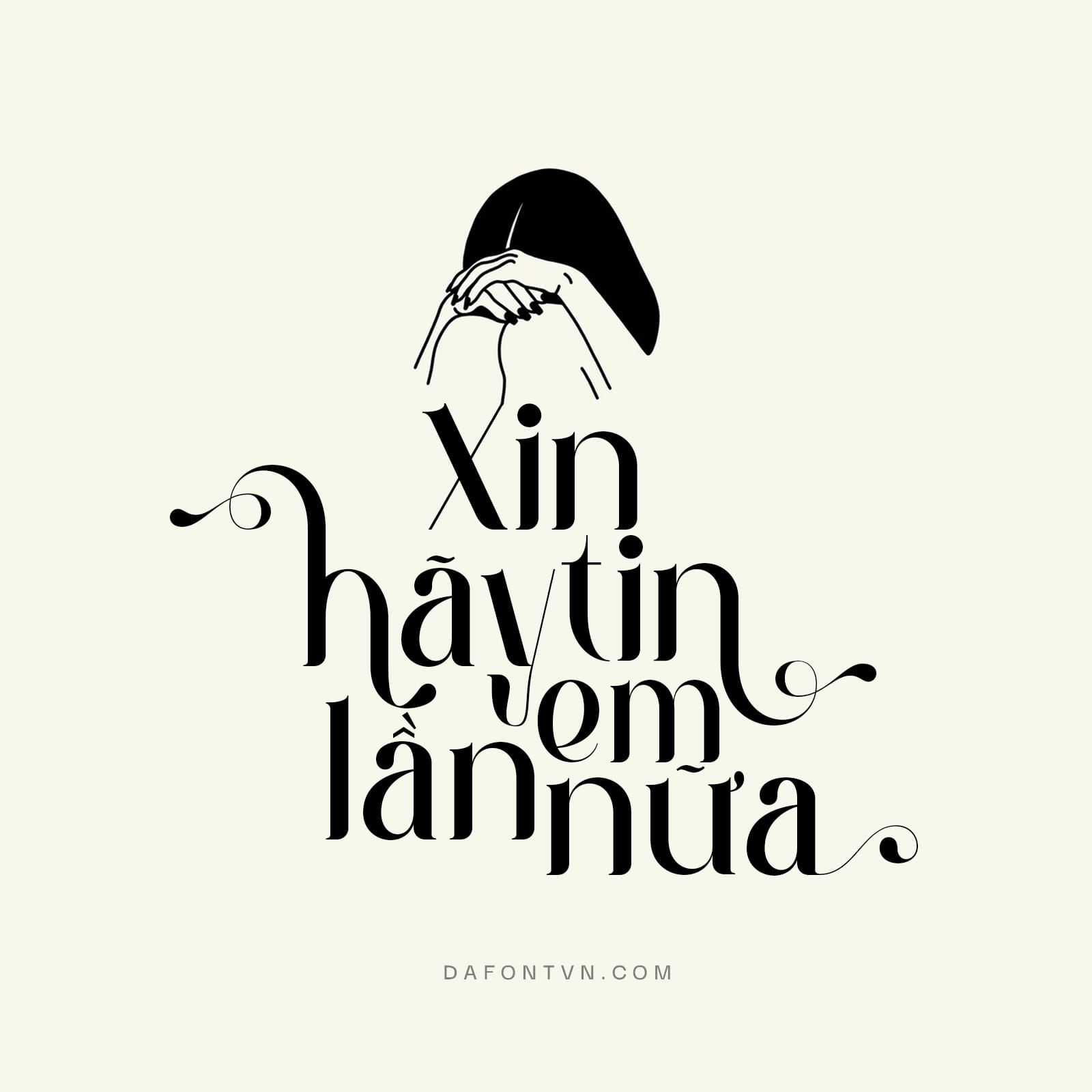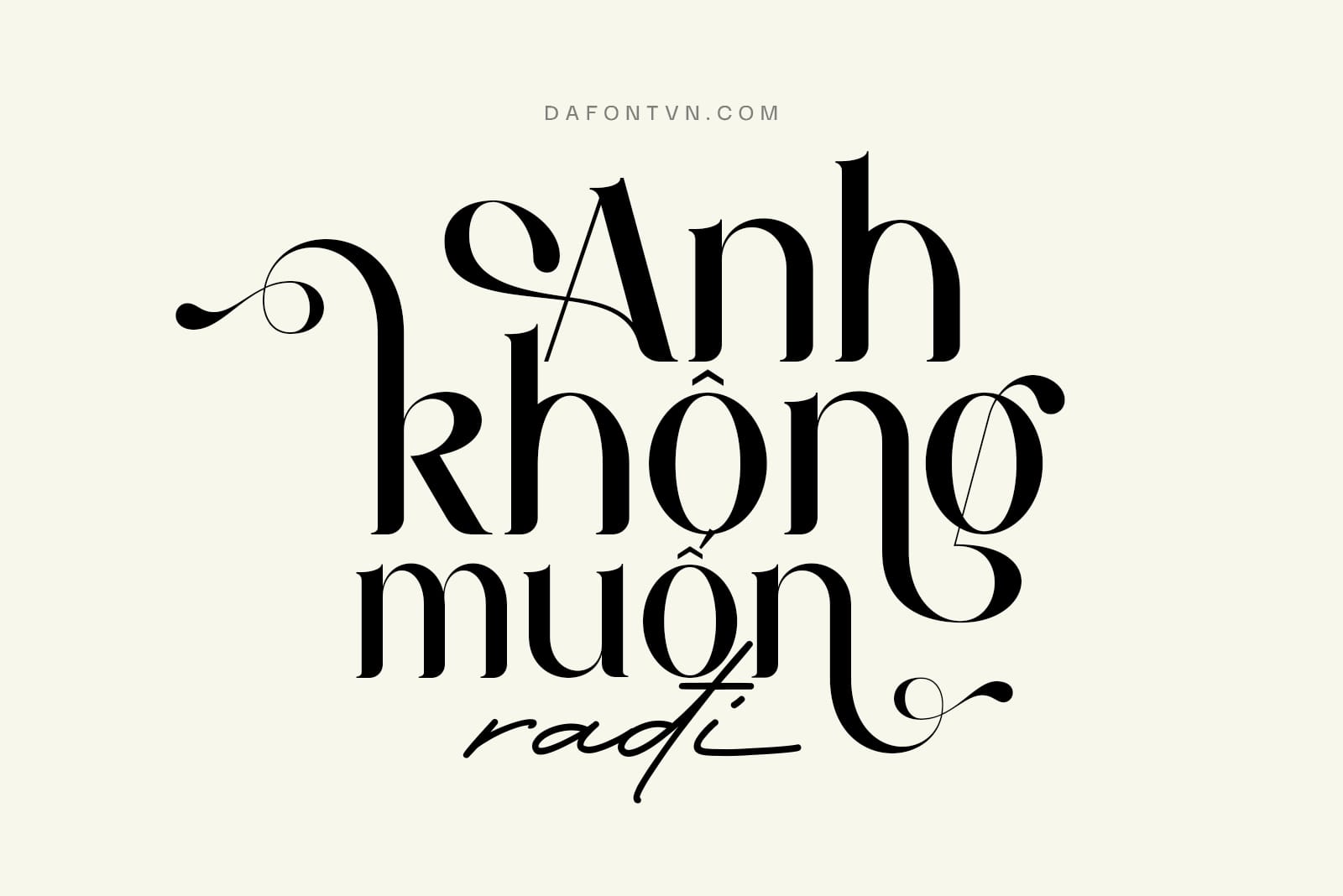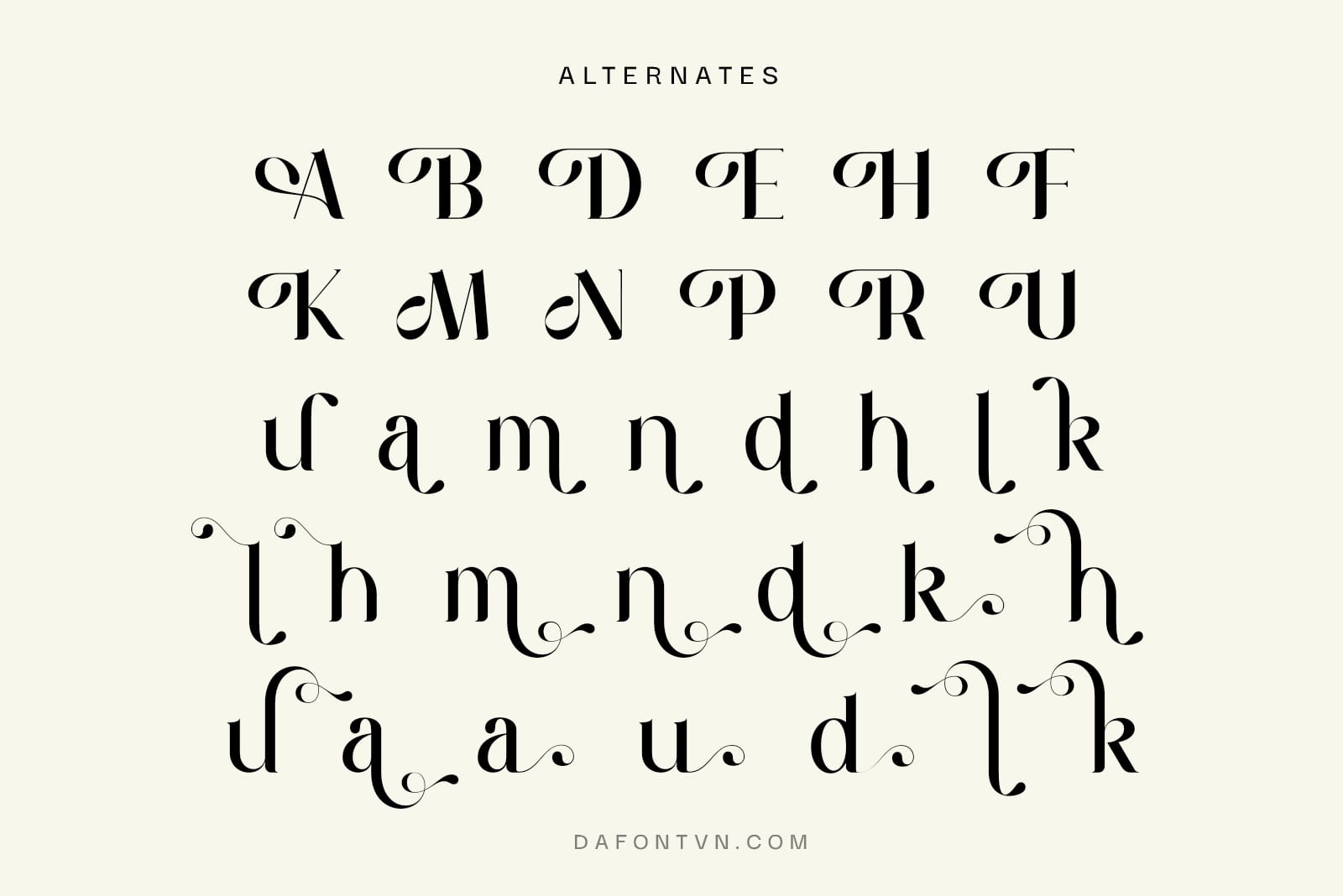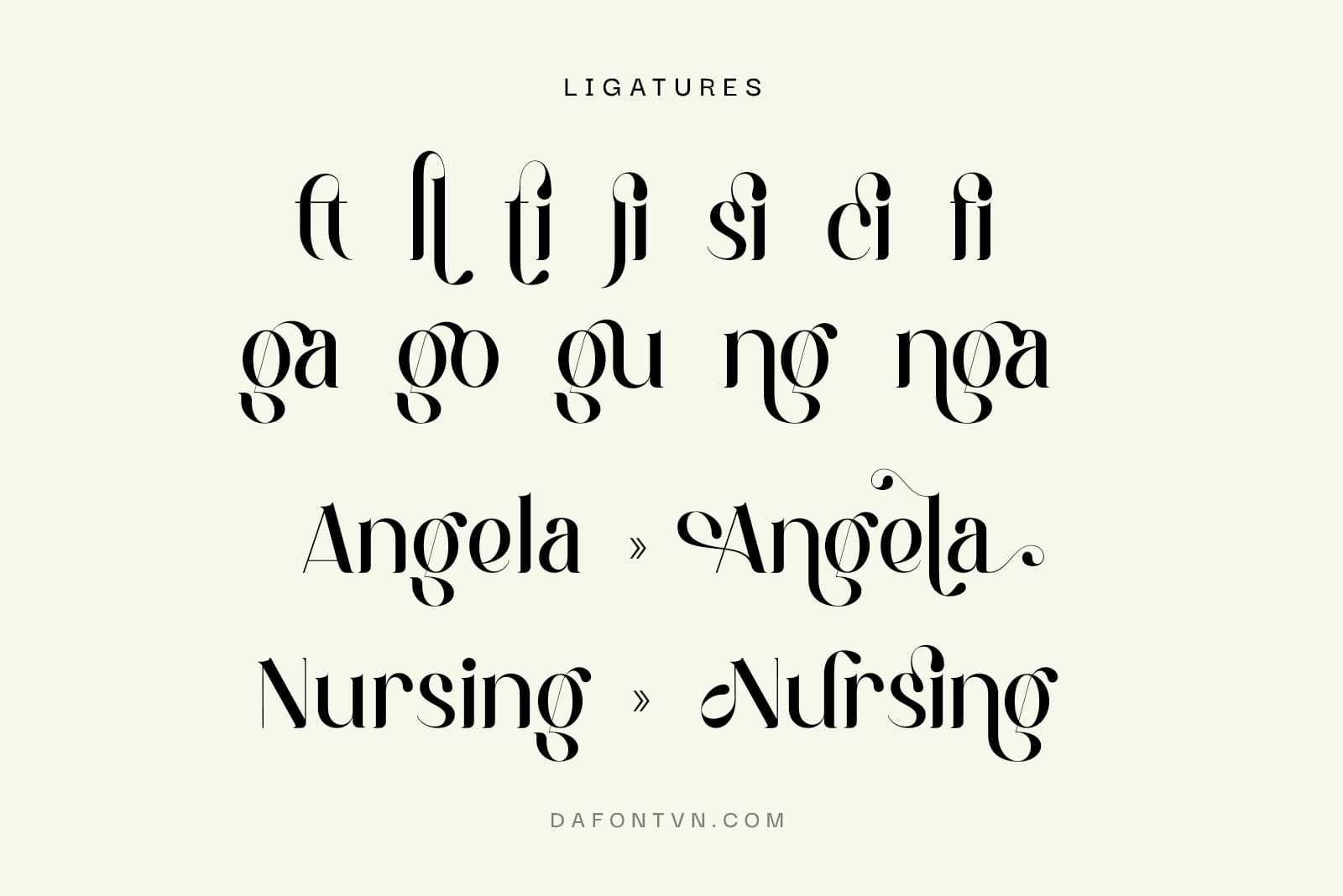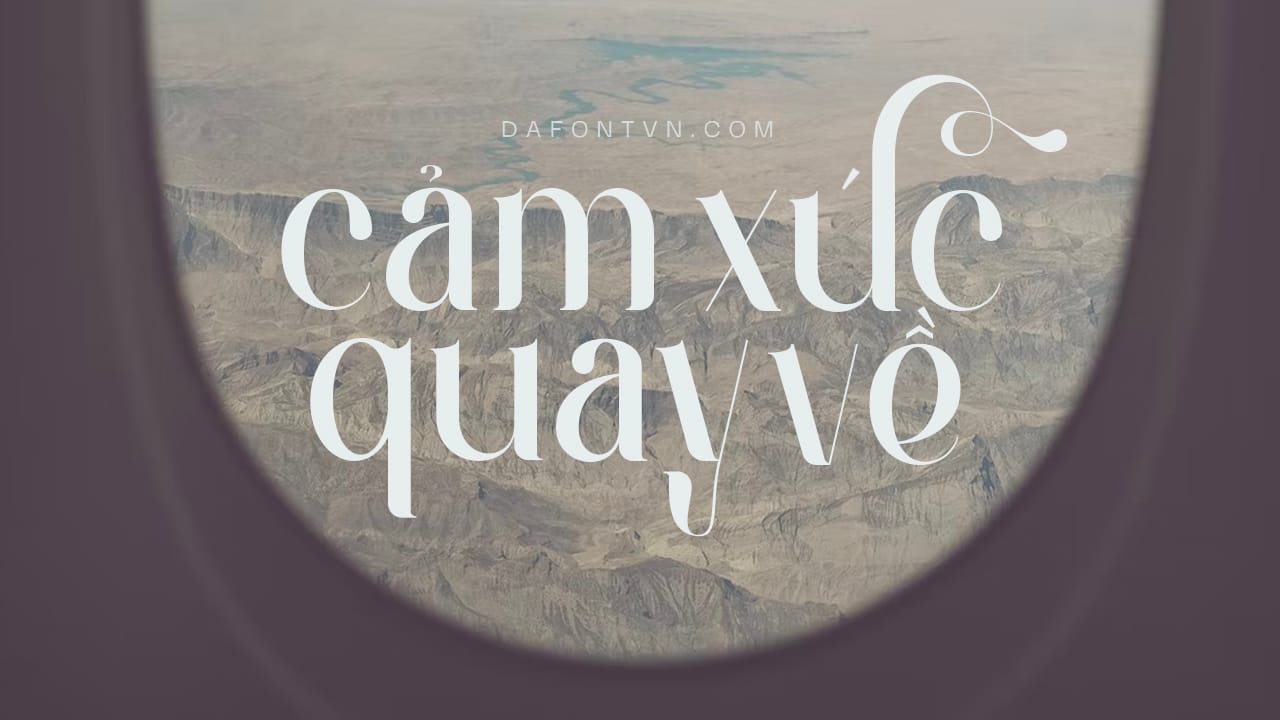
Maung Font – 1 kiểu serif hiện đại, mới mẻ và tuyệt đẹp được thiết kế ấn tượng và đặc biệt hơn font chữ còn có thêm các chữ ghép và các chữ xen kẽ có thiết kế uốn lượn mềm mại, độc đáo giúp tăng thêm nổi bật cho các tác phẩm của bạn.
Font Maung Việt hóa phù hợp cho nhiều các thiết kế như xây dựng thương hiệu, thiệp mời, quảng cáo, typography, bìa sách, tạp chí… Bạn hãy thử kết hợp Maung với các kiểu
khác để có những thiết kế đẹp hơn nhé.